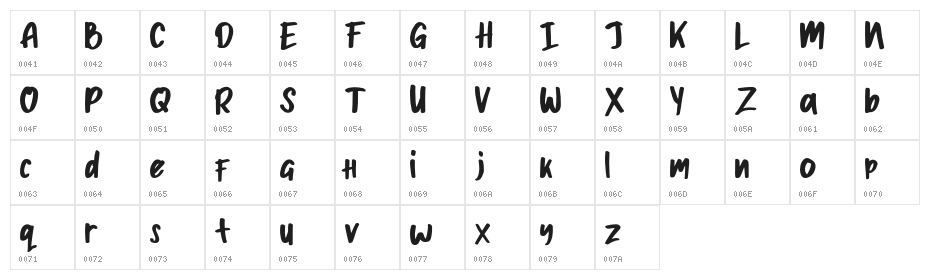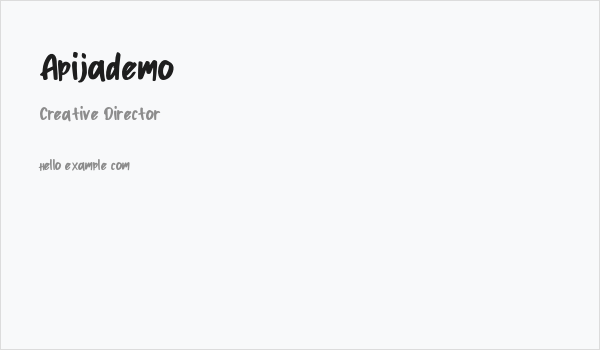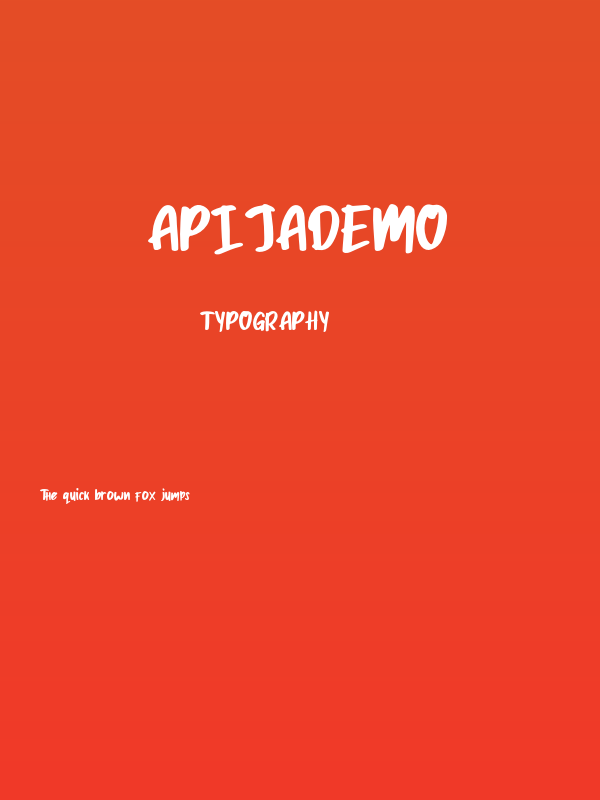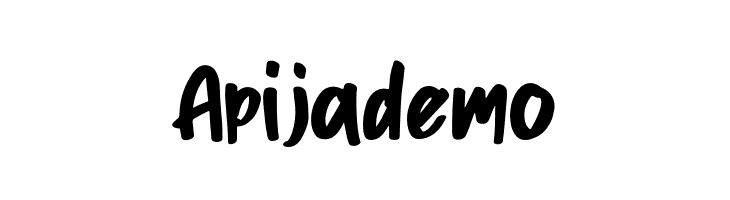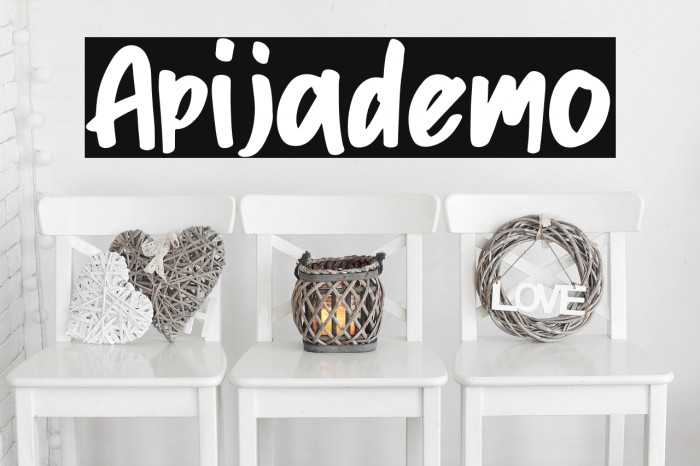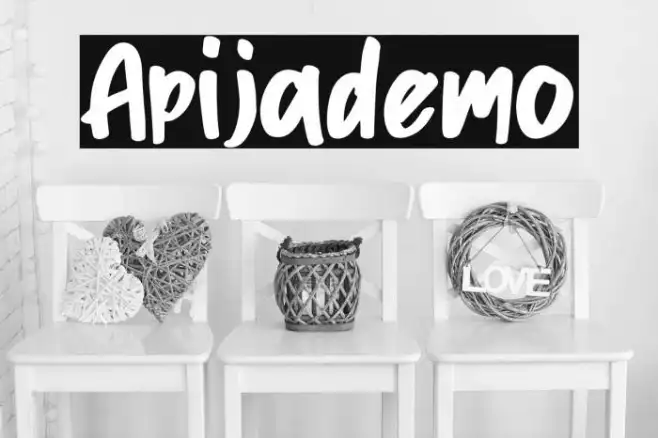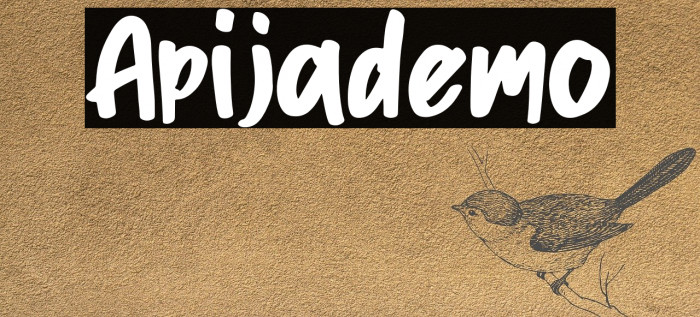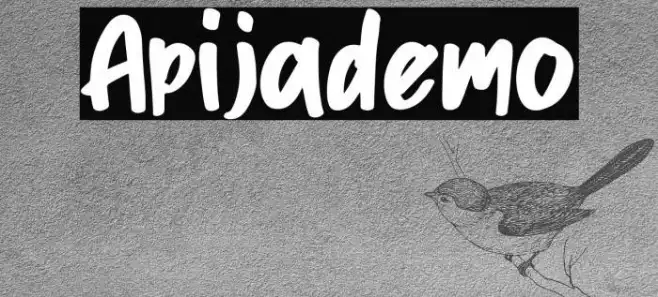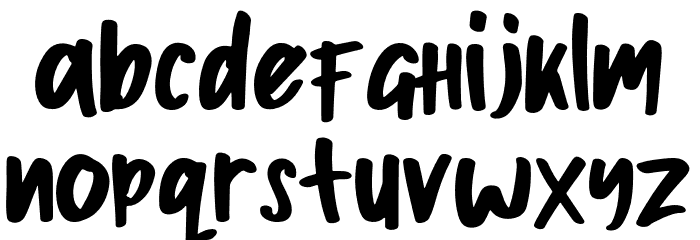
Apijademo Font
✎ Cartoon
| Style général | Casual and playful |
| Cas d'utilisation | Headlines, Logos, Social media graphics |
| Projets proposés | Ideal for greeting cards, posters, social media graphics, and branding projects that require a personal and informal touch. |